30 个最佳复古字体集合
已发表: 2022-06-25最好的复古字体集合,您可以使用它们为访问者提供出色的体验。 Vintage 和 Retro 风格的字体是常青树,在您正在处理的任何项目中看起来都很棒。
吸引注意力的最重要的事情是引人入胜的文字,如果使用恰当和梦幻般的字体在线发布内容,文字的影响会增加。
我们都知道基本字体,但除此之外,您还可以使用更多的字体来实现您的目的。
因此,在这里,我们将介绍 30 种具有复古特征的此类字体。
惊人的复古字体集合
安斯利显示器
要讨论的第一个字体可以免费下载,可用于商业和个人方式。 它结合了现代和复古的排版,突出了展示的吸引力,适用于标题。
铸铁字体
这是一种浓缩的复古字体,是一种免费字体。 它可以在商业上用于服装、客户等。设计师杰里米·瓦西(Jeremy Vassey)为他的创作赋予了几何结构,这对于创建给人留下深刻印象的标志很有用。
Hustlers Rough 演示字体
这是 Decade Type Foundry 的复古演示字体,仅供个人免费使用。 商业版有两个品种——粗糙和干净。
它还具有 300 多个字形插槽,其中包含欧洲口音的独特字符。 也可以购买此演示的许可证。
Duwhoers Brush Free字体
印度尼西亚设计师 Agga Swist'blnk 试图将复古与现代相结合,制作了这款字体。 你会得到一种复古的手工感觉,但使用刷子的效果是一种现代感。
Graphique Pro Next Comp
此设计属于瑞士著名设计师 Graphique Pro,出生于 1945 年,Hermann Eidenbenz。 设计师的基本想法是制作更多的阴影效果,给人一种层次感。
这个想法是为经济和时尚的标题创建一种字体。 随着最近分层字体的趋势,他的想法更加最新。
Profont 工作室现在将 Graphique Pro 的想法提升到了一个新的水平:Graphique Pro Next。 分层类型系列由 8 种样式组成,可以结合多种方式来创造独特的设计。
家族中的这些字体可以排列和重新排列在一起,以产生不同的效果。 上述版本是免费的,但对于其他类型,您将需要支付 39 美元。
要点粗略
Yellow Design Studio 诞生了 Gist Rough,这是 Gist 的凸版印刷版本。 这个房子里有多种字体,每一种粗细都有三种:超粗体、超粗体两种和超粗体三种(这些是苦恼的选择)每个粗体有 627 个字形,以及细节、纹理、风化的感觉字体使它成为一个有趣的选择。
这种字体可以很简单,也可以充满装饰,如花饰、连字或某些风格化的集合和一些特殊的字母,赋予那些更时髦的感觉和与生俱来的风格。 内联层使它更具吸引力。 有不同的类型,可以以 20 美元的价格享用。
黑色
Matthias Guggisberg 是一位瑞士设计师,他创建了这个包含 12 种字体的 Sans Serif 字体系列。 在这种几何字体中可以找到 20世纪初的味道。 人们可以在这种字体中找到大量和轻型的设计。
这种字体可以免费使用,并且是很好的专业用途,并且对希腊语、西里尔语和拉丁语有一个值得一提的命令。
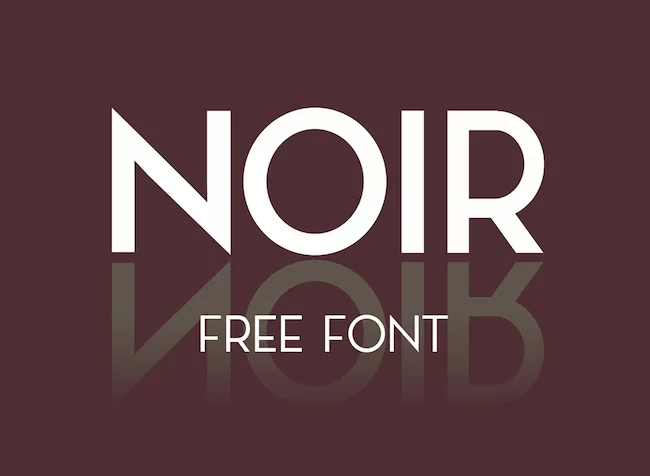
激光 84
这是来自巴拿马 Juan Hodgson 的设计师绘制的另一种免费字体。 由于使用了画笔效果,这种字体具有 1980 年代的复古感。 口音、符号和数字都可以在这里找到它们的用途。
萨博
这是一款以像素风格为主,带有国际口音的复古字体。 该字体有两种类型——填充型和内联型,由 Philippe Moesch 设计。
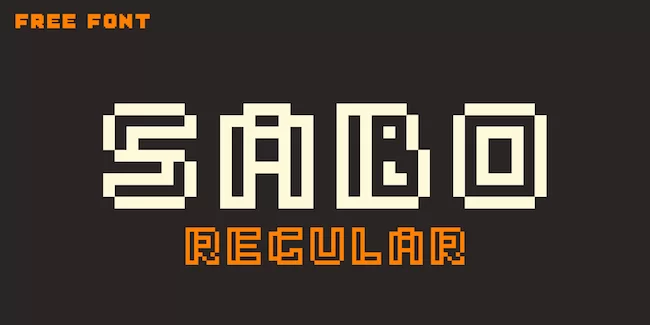
Alt 复古
来自塞浦路斯的设计师 Andreas Leonidou 用粉笔画出了这种复古风格的字体,其特点是多条线条,有五个粗细。 此字体可用于图形设计应用程序。
五种类型是:Alt Retro、Alt Retro Black、Alt Retro Thin、Alt Retro Bold 和 Alt Retro Light,所有这些都是免费的。
街头服饰
如果您想为您的标志或设计增添 60 至 70 年代的复古外观,请选择街头服饰。 它大胆而时尚的方法使其对用户可行。 这是一种有趣、运动的字体,Artimasa 制作的独特假期非常适合包装、品牌、T 恤、海报、徽标等。
使用 Indesign 和 Adobe Illustrator 可以使用这种字体的各种替代字符,它们是一个开放类型的精通程序。
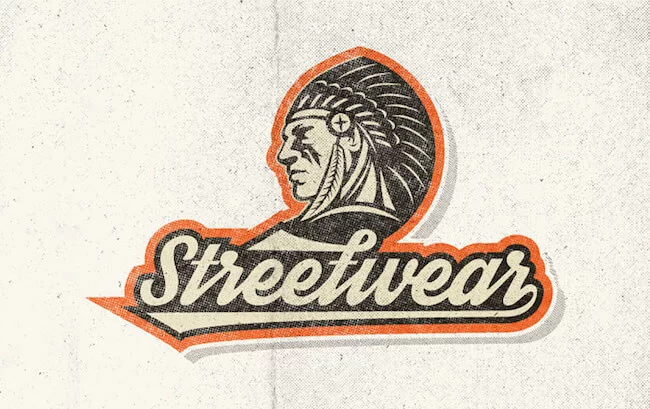
临街
一种外观漂亮的复古字体,有多种粗细可供选择。
典型的
要通过排版获得野餐的感觉,请选择 Typnic。 该系统收集了许多不同风格的字体。 其标题样式具有六层字体,可用于多种组合,以获得强大的标头和标题。
它设计有十八种变体。 所有这些都可以结合起来获得混合输出,这将有助于吸引更多的观众。 这是手写的,使用了 18 种不同的字体和三种风格,它们彼此不同,但也很恭维。
此外,还有其他选项,如装饰物、装饰品、标签和图案来美化作品。 这可以用于各种项目,并且对于广告非常有效。 标题选项是免费的,其他选项为 9.98 美元。
光之镜
这是一种带出 20 世纪银幕怀旧情怀的字体,在德国,20 世纪的电影院就是这样称呼的。 Stefan Huebsch 是重现这种电影魅力的设计师。
总共有五个魅力,其中两个是斜体。 霓虹色的使用增强了基本的展示风格,您可以使用霓虹灯创造出更多令人兴奋的设计。 取决于此,屏幕学分是基于的。 在所有类型中,Trailer 字体是免费的。
星期日
顾名思义,这种字体代表了周日悠闲的氛围。 这款字体具有所有大写字母和手写感,可免费满足商业和个人需求。
来自希腊的 Anastasia Dimitriadi 是设计师,这里使用的语言是希腊语、拉丁语和西里尔语,此外还有字母、符号、数字和替代字形。 此字体免费提供,但欢迎捐赠以改进它。
浮子字体
字体也可以受到摩托车的启发。 Bobber 就是这种情况,这是一种具有独特的基于网格和模块化风格的字体。
共有三个版本:传统版、纯色版和浅色版——所有这些版本都采用全大写字母和交替的平板衬线字体。 此字体字体中包含各种语言,如希腊语、冰岛语、俄语、塞尔维亚语。 有两种类型的版本 - 免费和付费。 您可以花 5 美元获得专业版。
门施
Mensch 是由 Morgan Knutson 设计的浓缩字体。 这种字体有四种粗细——内联、细长、粗体和规则,这使得它在使用中变得多样化。
奥威尔式
灵感源自乔治·奥威尔在其巨著《十九八十四》中探索的概念,并遵循亨利·卡斯隆的意大利模式。 它于 2014 年 12 月由 Lost Type Co-op 出版。
这种字体是反向强调的,用于显示。 由印度人 Shiva Nallaperumal 设计,可通过按需付费许可证用于个人用途,但商业用途则必须支付 35 美元。
胡佛维尔
一种整洁、干净、前卫的字体,具有 1920-1930 年的感觉,被认为是其复古品质,可以免费供个人使用。
美国队长
受令人敬佩的美国队长、国家的救星和伟大的捍卫者的启发,迈克尔·阿德金斯创造了这种字体,类似于那个人的力量、勇气和决心。 由于这可以追溯到 1940 年代,因此它具有复古的气息。
有两个权重,但如果你有商业许可证,你可以得到所有六个品种的全套字符。 此字体支持的语言是西里尔文和希腊文。
Sho-Card-Caps
设计师尼克柯蒂斯声称这种字体的灵感来自于过去手工制作的海报。 1930 年,有一种名为 Futura Display 的字体起到了灵感的作用。 这种免费字体非常适合头条新闻。
克林克斯
它是一种带有设计字母的字体,给人一种复古的感觉。 它由 Mans Greback 设计,非常时尚。 对于个人使用,不收取任何费用,但对于商业用途,有可用的许可证。
很多
设计各种项目(如印刷品、网页、运动、服装、T 恤等)的首选是这种字体,它具有角度几何图形。 虽然这可以免费享受,但捐赠不会造成任何伤害,而是有助于增加投入并有助于保持多功能性。
火柴盒
这是字体艺术家 Simon Walker 的第一款字体。 这种字体有两种形式——常规字体和纹理字体。
圆角衬线和扩展图形是这种字体的特色; 它在头条新闻中赋予了个性和独特的基调。 您可以根据个人需求按需付费,并享受 30 美元的商业许可证。
韦斯顿
为了使标题和徽标更有趣,Pavel Pavlov 创造了这种全大写字体,并且版本规则且轻巧。 它可以免费下载。
如果您想使用整个字体系列,则必须购买商业许可证。 该字体的外观经过排序,并具有所有主要类别:内联、黑色和粗体。
手店排版
Fontscafe 的创作是四种类型的组合包,所有这些都具有复古手工制作的感觉。 供个人使用,它是免费的。 这可以用来制作有趣的添加。
TT Masters 演示 黑色
如果你想给咖啡店带来清爽的感觉,那就去 TT Masters 和它的变种吧。 四种不同的风格是 Masters Condensed、Masters、Masters Rough 和 Masters Birds。
所有这些类别再次细分为薄、轻、常规、粗体和黑色。 在所有现有的品种中,Demo Black、Demo Rough Thin 和 Demo Birds 都是免费的。 其他费用为 25 美元。
萨武浓缩
由于其手写字体的感觉,这种字体是展示的最佳选择。 推荐用作显示字体,字体有四种样式 - 常规、粗体、浓缩和浓缩粗体。
精简版可免费使用。 这也是一个全大写,整洁的创作。
环境
Environ 是一种具有圆形结构的模块化字体,由 Matt Desmond 设计。 由于这种字体是使用多行创建的,因此它对小文本有奇效。
小字号的小字块是使用这种字体的最佳方式。 总共有六个重量,并且只能免费使用。
梅康
该字体由 The Northern Block Ltd. 编写。Jonathan Hill 集思广益,创造了这个具有复古吸引力且相当重量级的字体系列。 该字体系列适用于服装、T 恤、网页、印刷品、运动等。
总共有四种类型,三种不同的选择。 特色是可以手动编辑的欧元符号、欧洲字符集和字距调整符号的存在。
介绍
Intro 是一款漂亮的复古字体,可免费用于个人和商业用途。 您可以从 FontFabric 下载此字体并在您的项目中使用。
该字体为您提供超薄、薄、中等和粗体版本的字体。 因此,您将拥有根据需要的所有选项。
尼克萨
Nexa 是古老和现代设计的完美结合。 您可以在横幅、设计、徽标、广告牌和任何其他项目上使用此字体。 它肯定会给您的整体设计带来很好的感觉。
最重要的是,该字体可以免费使用。 整个 Nexa 字体系列包括9 种粗细和36 种字体。 但是,它们都不是免费的。
底线
这些是三十种字体,即使在现代,它们也会为您的设计带来复古和优雅的外观,但它们都以自己独特的方式呈现。